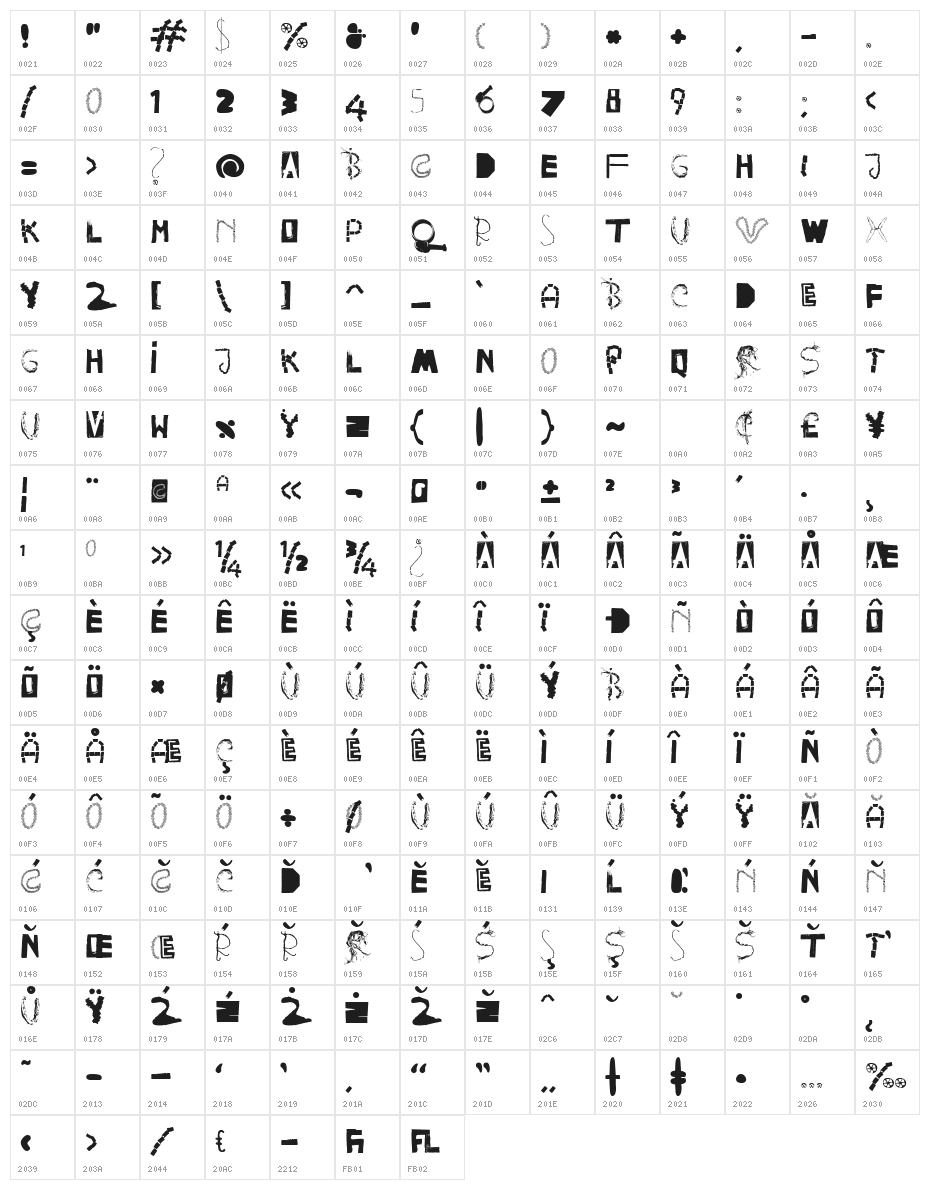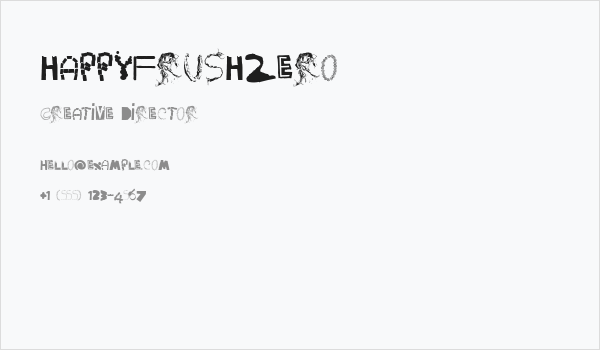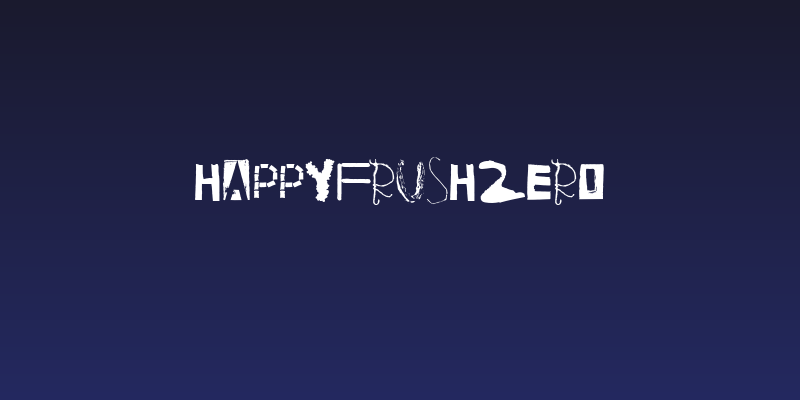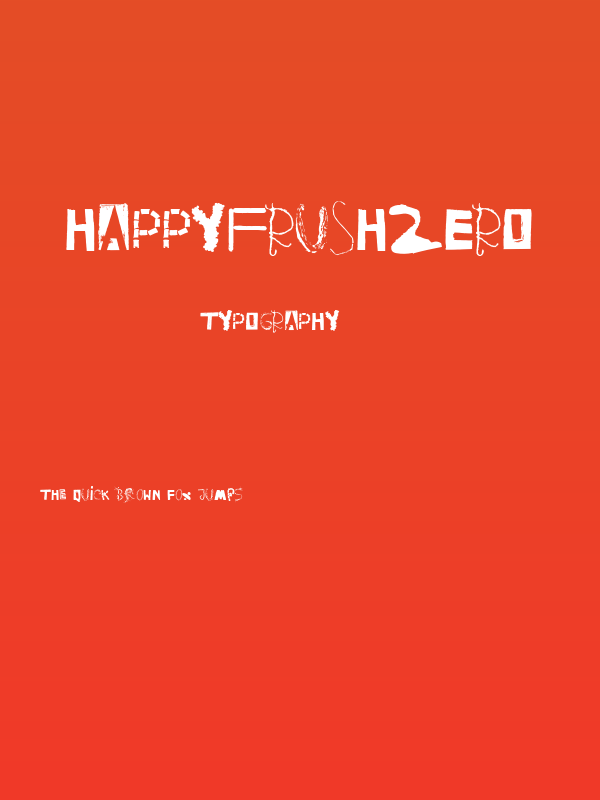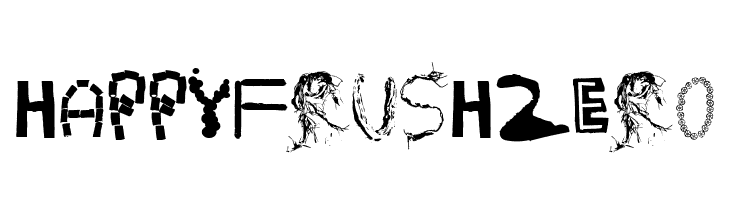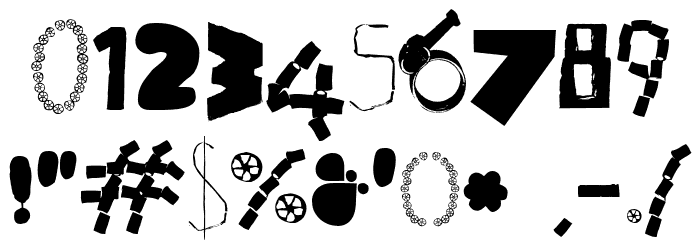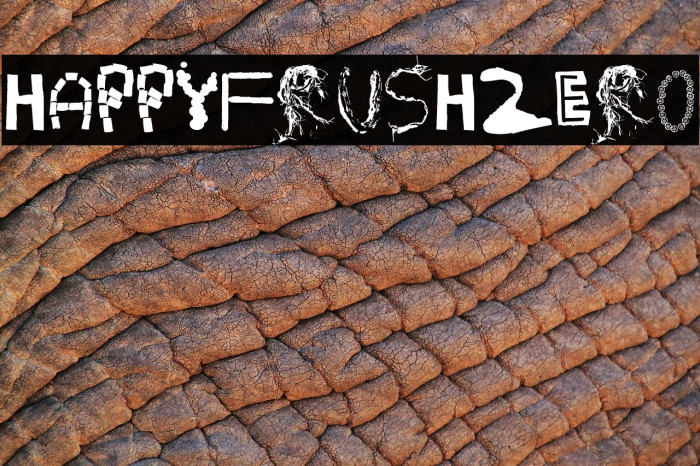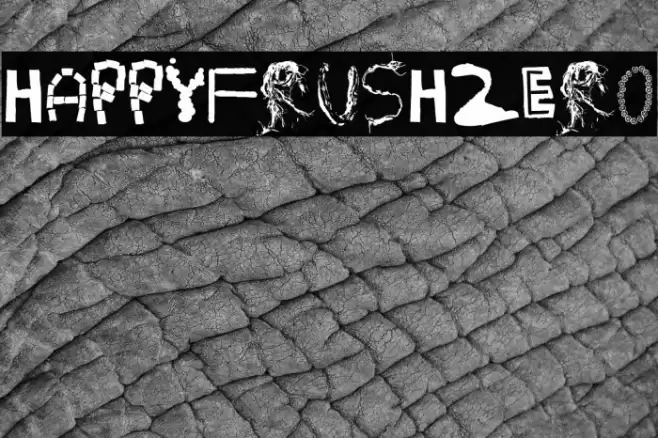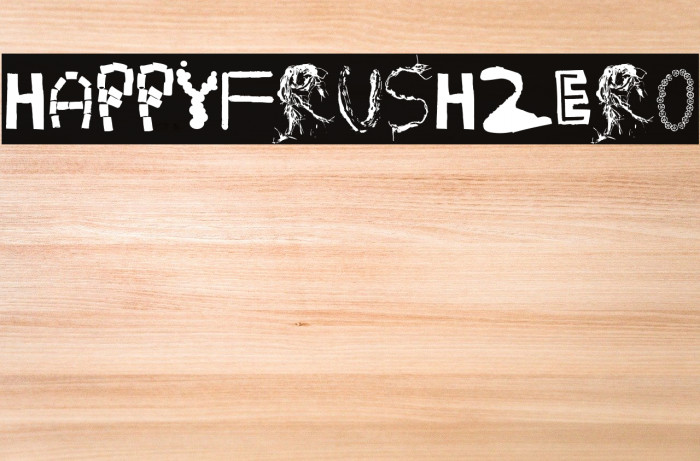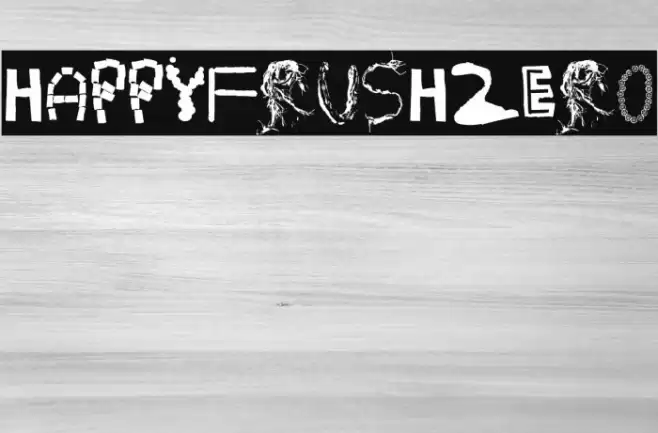
HappyFrushZero Font
✎ Decorative
| Область применения | Logos, Posters, Artistic Projects |
| Рекомендуемые проекты | Ideal for artistic projects, posters, album covers, and any design work that requires a bold and unique visual impact. |